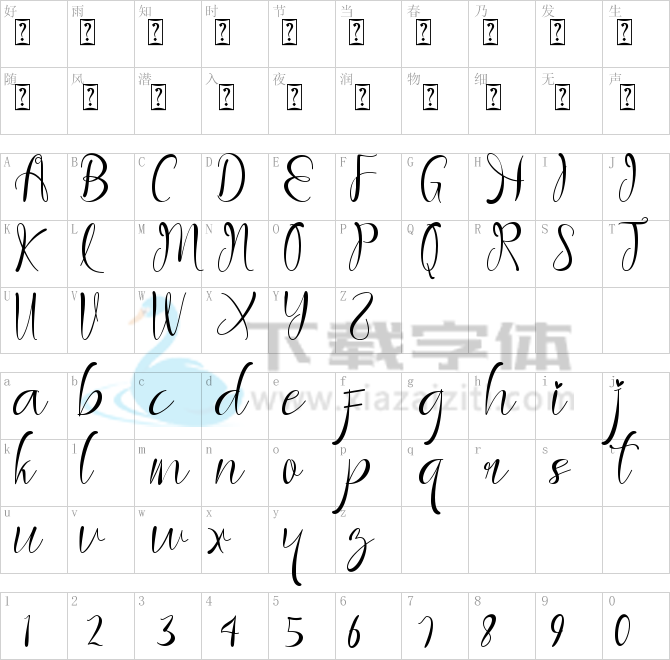
Amantha.otf字体下载
Amantha.otf字体下载,这款字体结构工整、笔画清晰,兼顾美观与易读性,适用于标题、正文、海报、包装、LOGO 等多种场景。字形优雅稳定,风格百搭耐看,适配日常排版与创意设计,让文字呈现更舒适、更具质感。Amantha.otf字体下载一笔一画,皆是细节,以均衡的比例、流畅的线条打造舒适视觉体验,字形端正大气,风格简约现代。无论是商业设计、品牌宣传还是日常排版,都能轻松驾驭,让文字更有格调与力量。Amantha.otf字体下载字体下载。